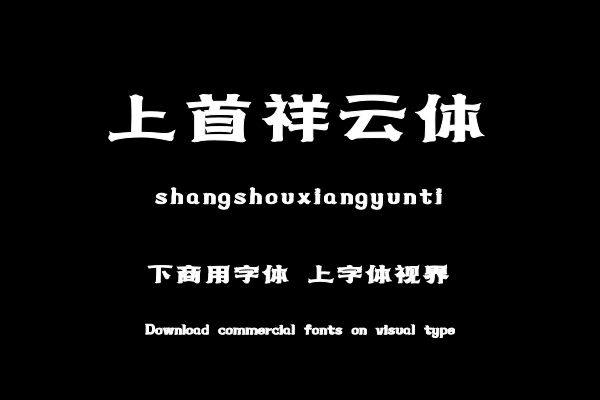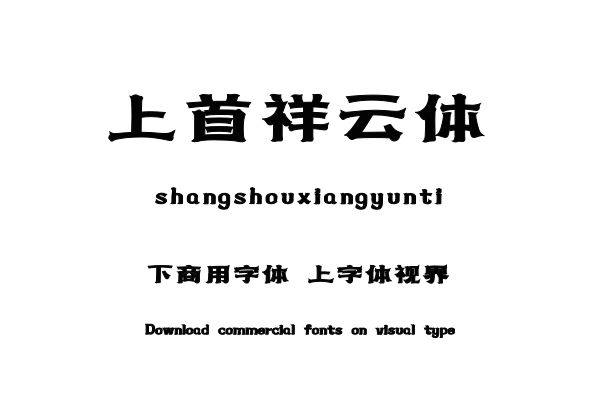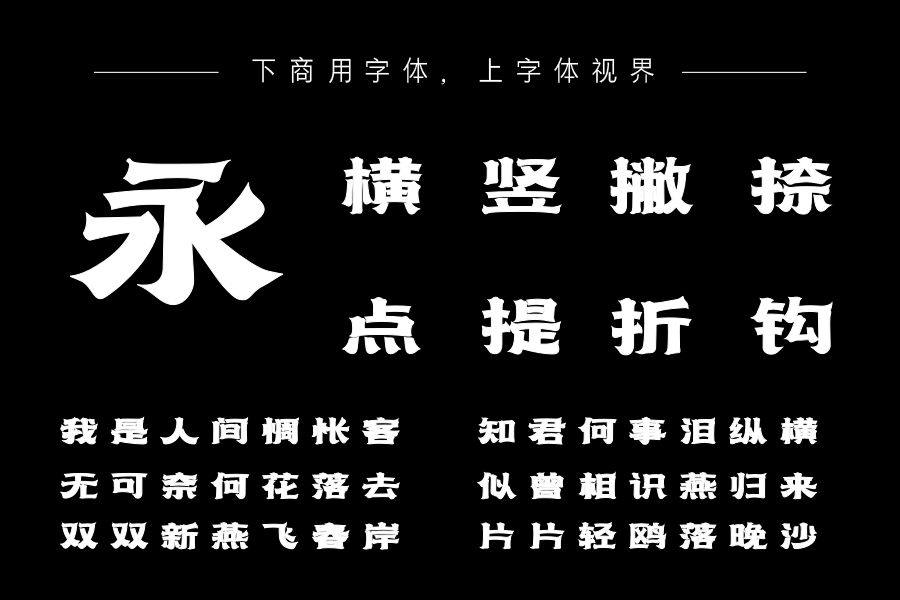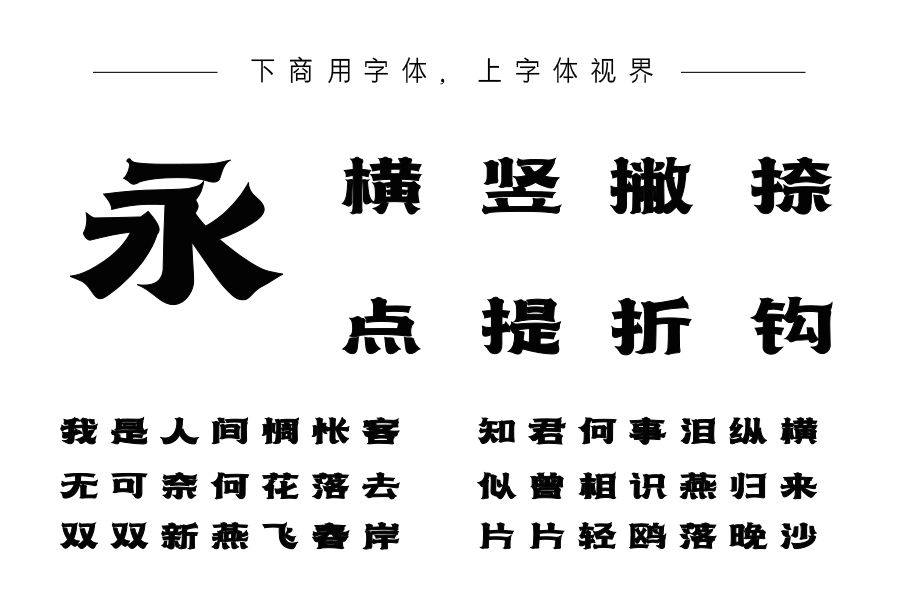
上首祥云体,字体在起笔和落笔处都有云纹形的设计,时尚和古典结合,线条柔美,曲中带直,直中带弯,透露出别致美感,刚柔共存,展现出非凡的特性,凸显力量感、流畅洒脱给......购买须知:“下载服务费”与“字体VIP”所获得字体 仅用于个人非商用, 商用请联系付费授权。本字体为电脑用字,手机没有root权限不支持直接手机换字(手机如何root,请自行百度搜索教程)。购买前请先 了解清楚后再付款 ,字体为虚拟产品无法回收 一旦购买不支持退款。